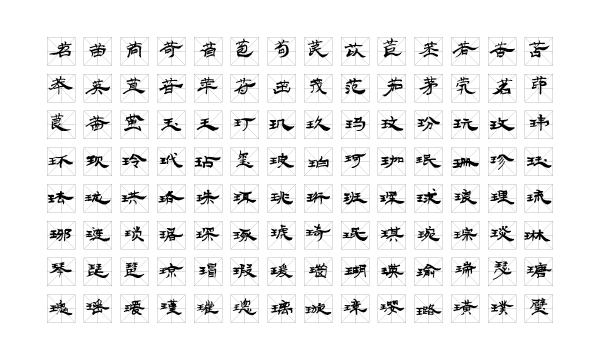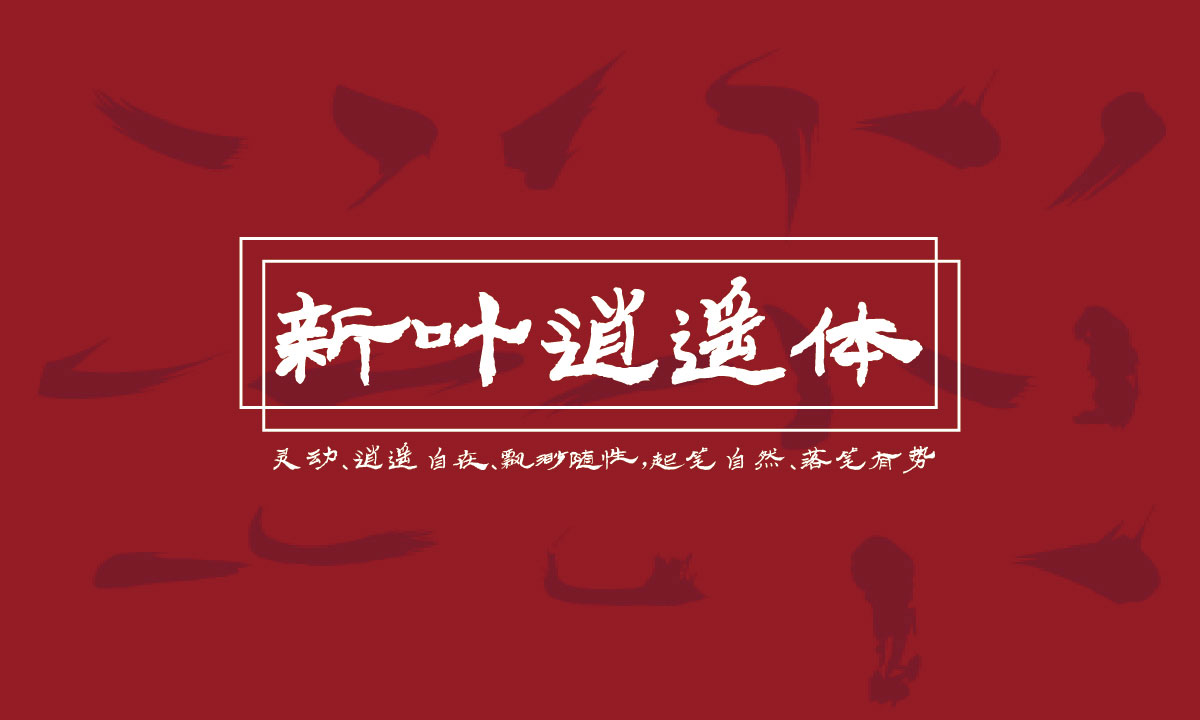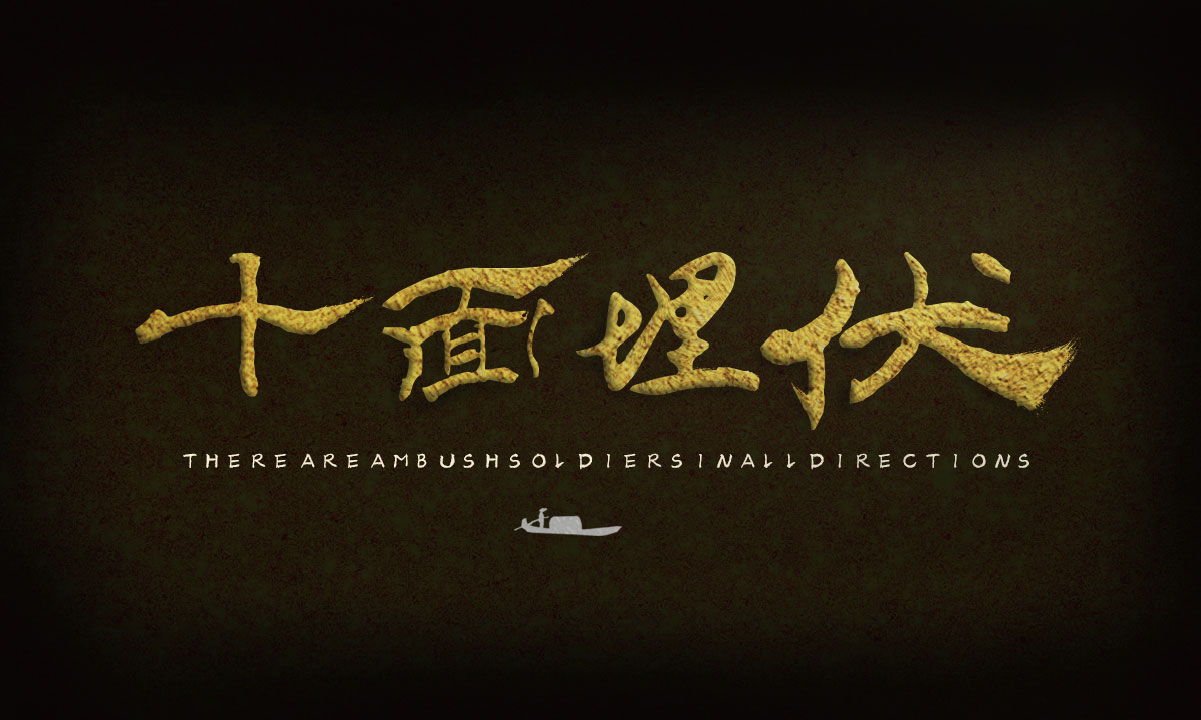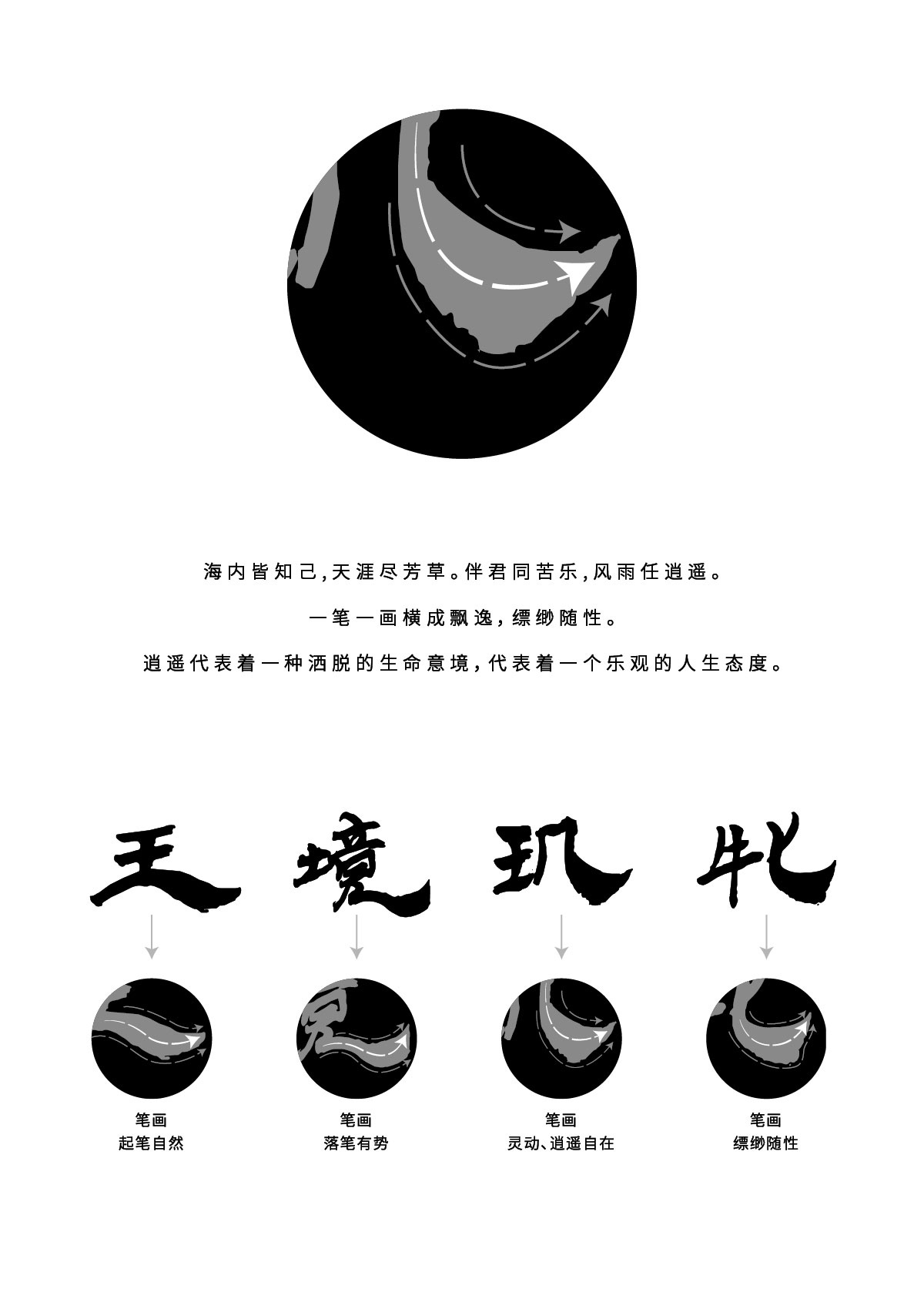
新葉逍遙體擁有靈動、逍遙自在、縹緲隨性、起筆自然、落筆有勢的字體效果,海內(nèi)皆知己,天涯盡芳草。伴君同苦樂,風(fēng)雨任逍遙。逍遙自古以來就是人們吟詠的對象,每個人都希望瀟瀟灑灑的過一生,無論是古代還是現(xiàn)代。逍遙代表著一種灑脫的生命意境,代表著一個樂觀的人生態(tài)度。我們期待著每個人都能以他喜歡的方式瀟灑的過一生,這就是我們創(chuàng)造逍遙體的愿景。
被困在高樓寰宇里工作,你有多久沒有好好看看外面的天空了,你有多久沒有咻一咻路邊的花香了。也許你會想逍遙離你很遠(yuǎn),可是當(dāng)你遇到逍遙體之后,你就會驚喜的發(fā)現(xiàn),這個字體是放在文字上的逍遙。當(dāng)你看到新葉逍遙體的時候,看著它一筆一畫的橫成飄逸,縹緲隨性,你心里突然蹦出扶搖而上九萬里的字句,你的心都開始跟著飄搖起來了。這就是逍遙體的魅力,讓你發(fā)現(xiàn)原來大廈高樓里,也存在你喜歡的逍遙人生。